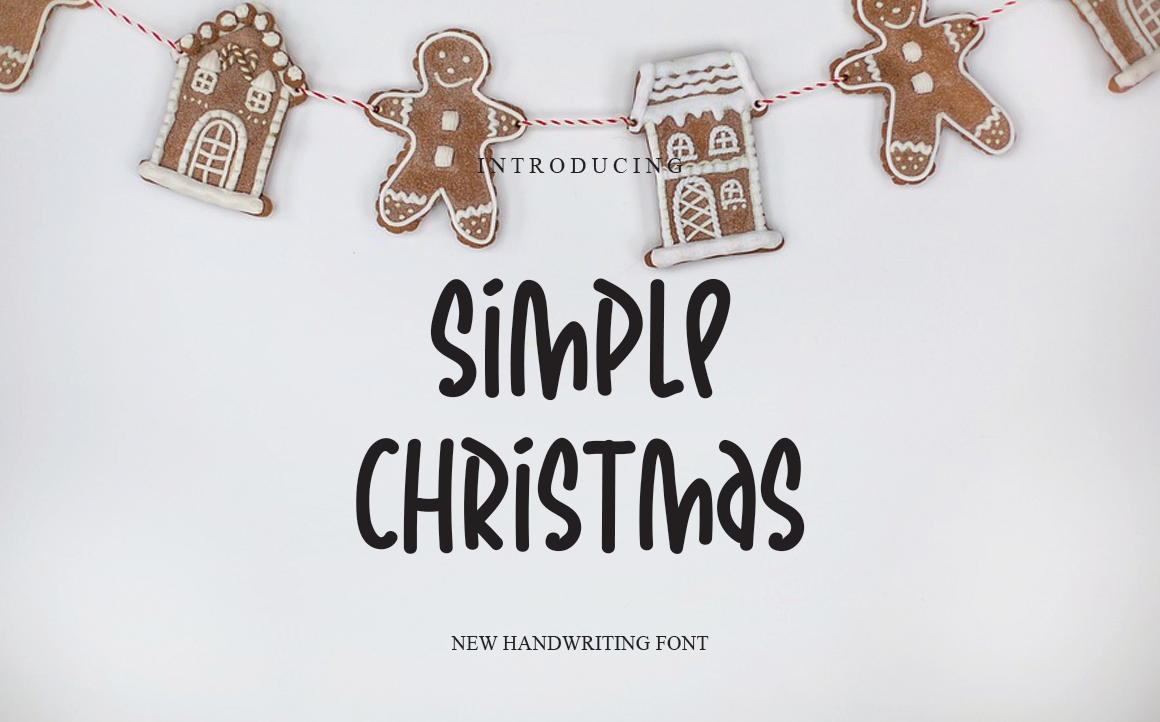
Simple Christmas Font – Download Grátis
A fonte “Simple Christmas Font” é uma elegante seleção entre as opções disponíveis no mercado de fonts para designers. Desenvolvida por LevinCreative e categorizada como fontes de exibição, essa fonte inovadora e amigável é perfeita tanto para utilização em redes sociais quanto para projetos DIY de escritura feita à mão. Ideal tanto para as suas próximas postagens nas redes sociais, seja para uma festa de natal única e moderna ou apenas um texto decorativo, quanto para aquela chamada que você está fazendo e deseja dar um toque pessoal e artístico, essa fonte não falha em transformar qualquer conceito criativo em uma obra-prima. Seu charme único, seu tom amigável e sua simplicidade única tornam esse design uma ótima opção para aqueles que buscam algo especial para suas criações de natal ou seus projetos DIY.